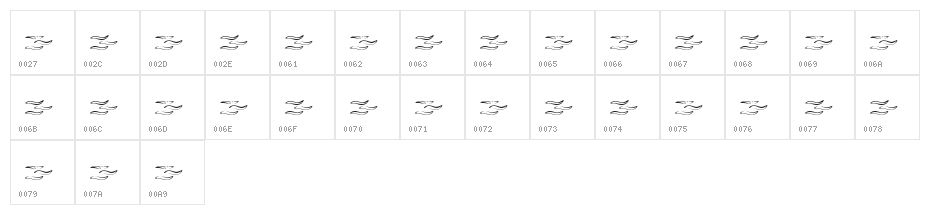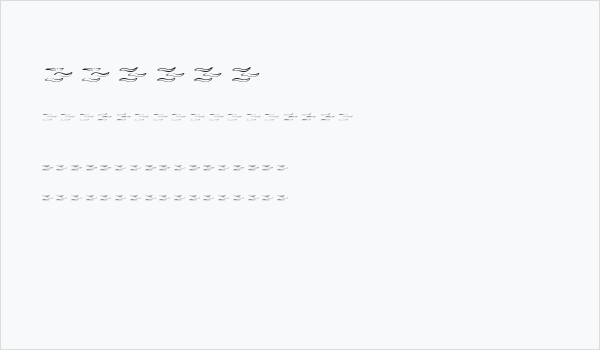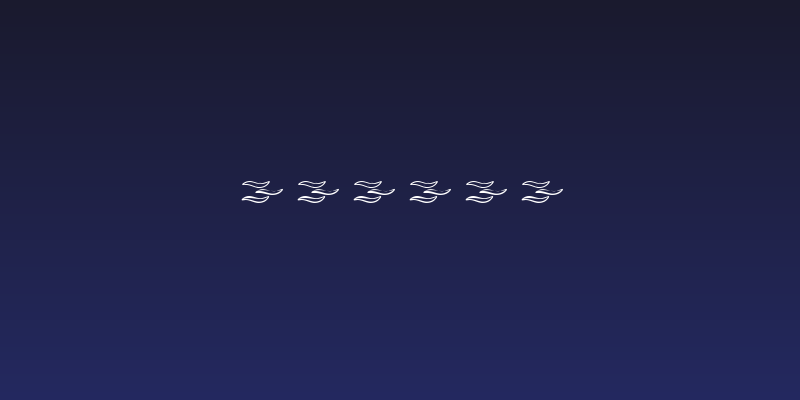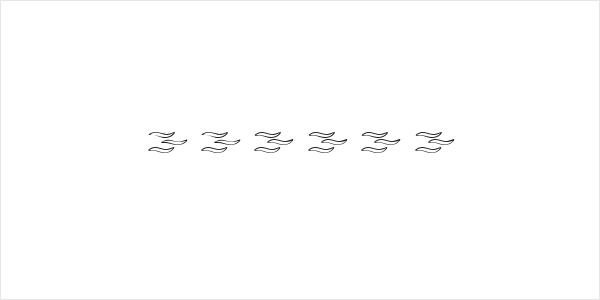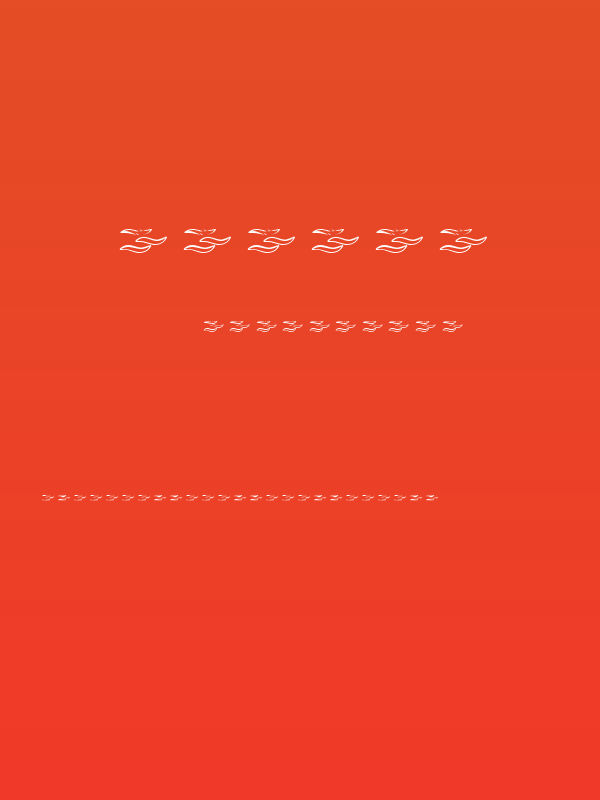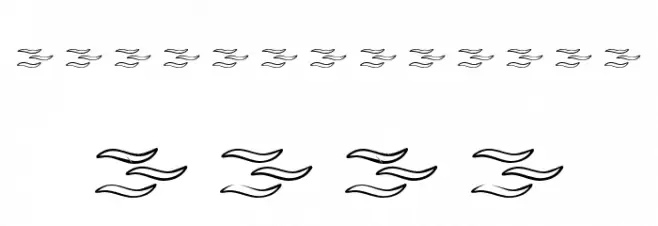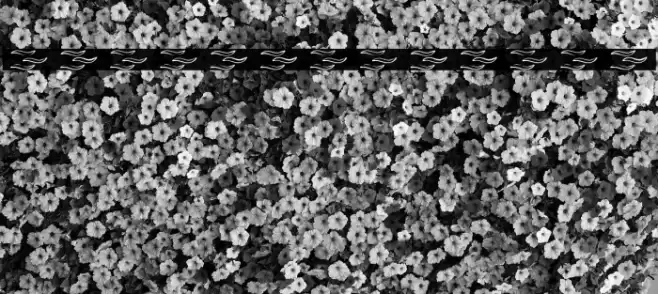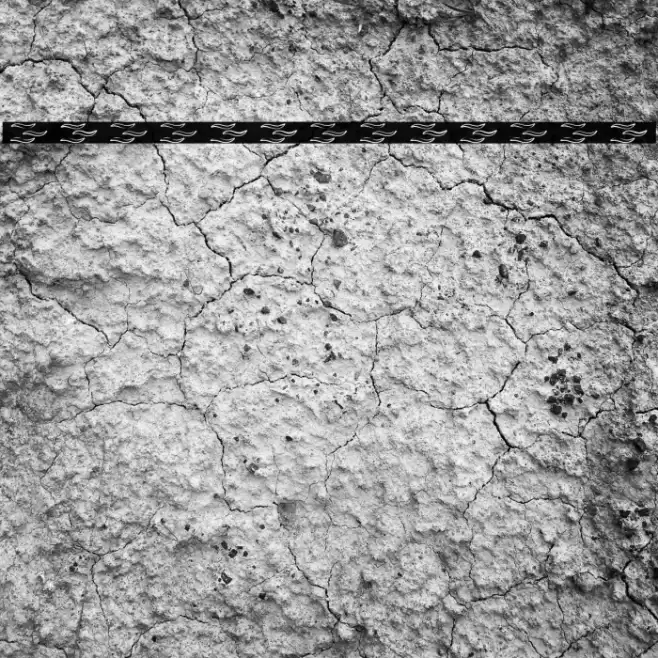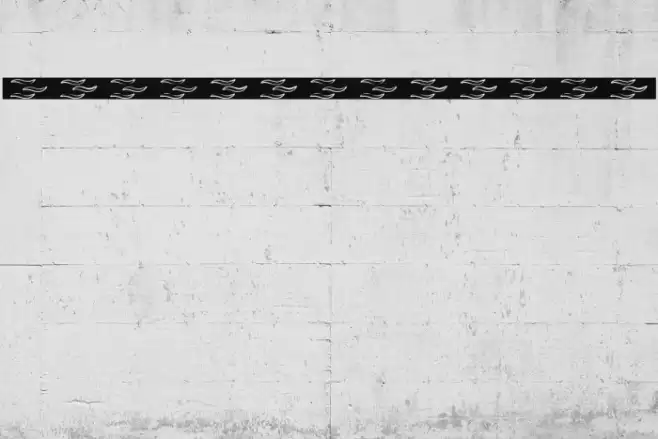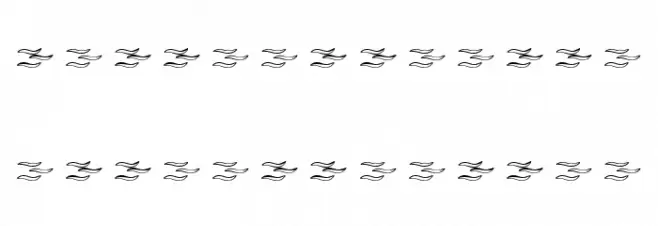
Sfockt Font
luxury got neat
| 用途 | Logos, Decorative elements |
| おすすめプロジェクト | This design could be used for decorative borders, branding elements, or as a pattern in graphic design projects. |